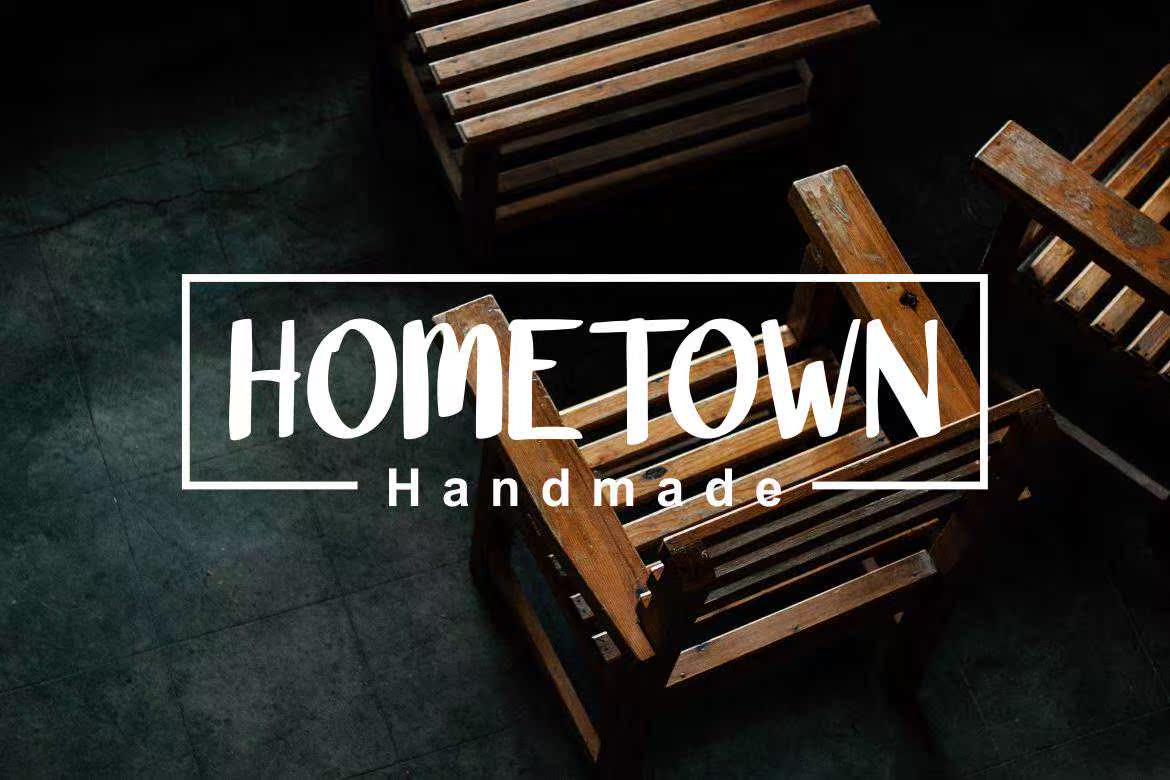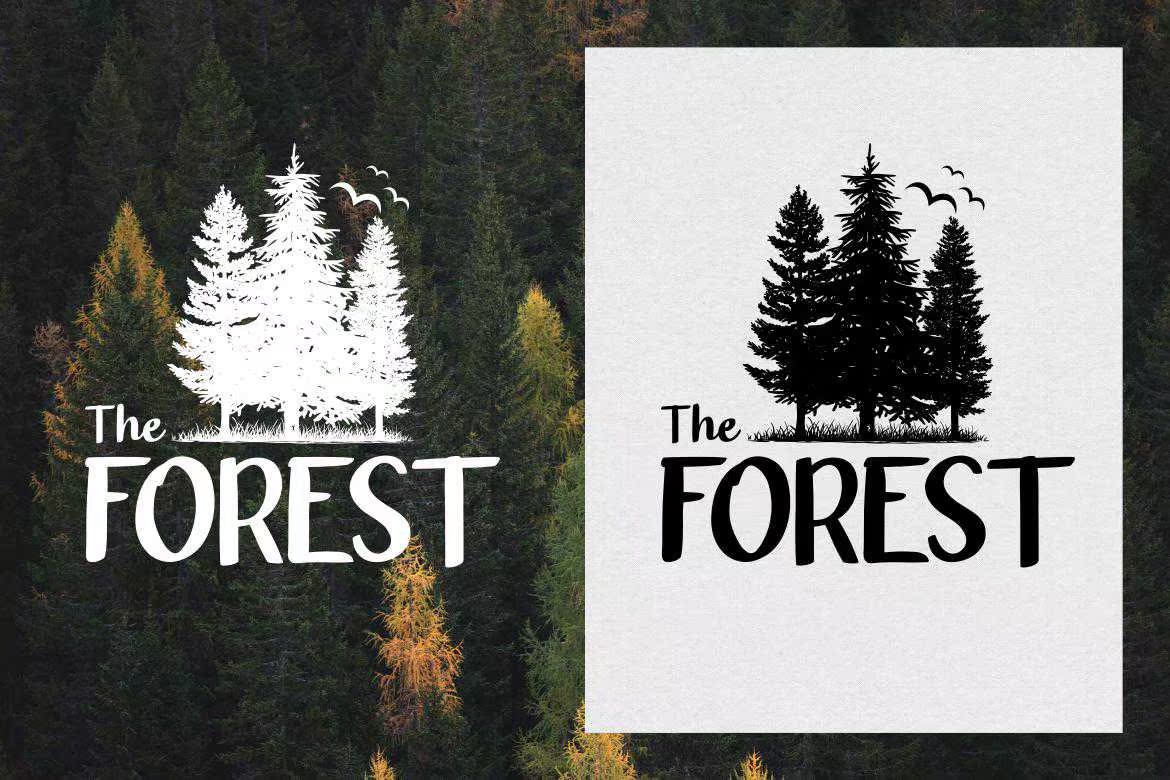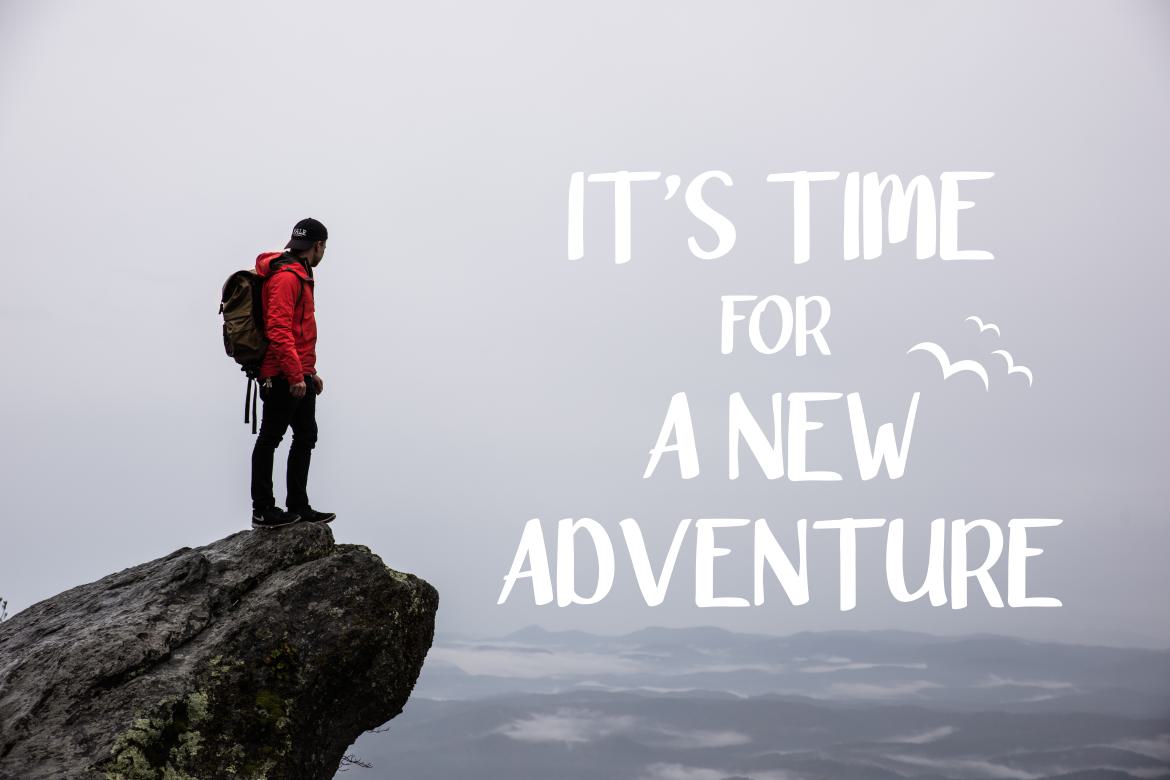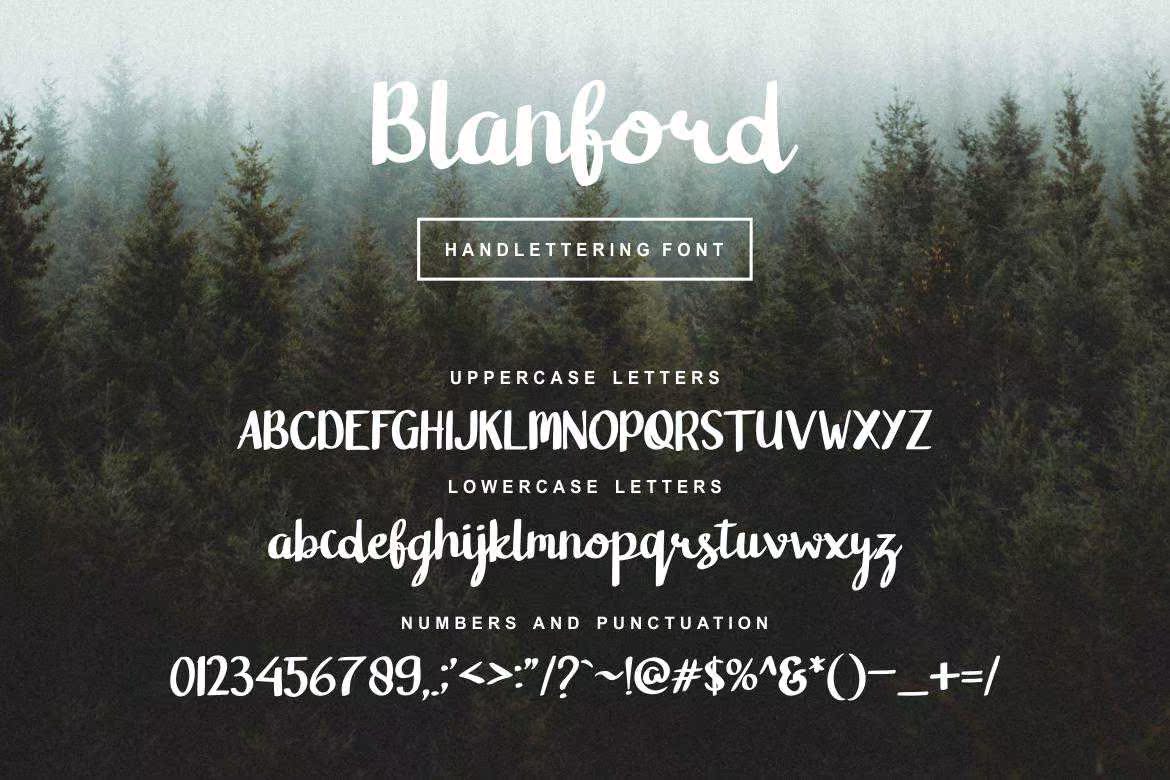
您好……介绍手写字体的平面图。此字体非常简洁、美观。非常适合用于徽标、服装、签名、网页主题、海报、报价、书籍或杂志封面等。您将获得:BlanfordTTF–大写和小写小写字母–标点符号和数字–分隔符和标准符号感谢您的检查,如果您有任何问题或疑问,请在网站上留言。您好…介绍手写字体。此字体非常简洁美观。非常适合用于徽标、服装、签名、网页主题、海报、报价、,您将获得的书籍或杂志封面等;——BlanfordTTF–大写和小写小写字母–标点符号和数字–分隔符和标准符号感谢您的检查,如果您有任何问题或疑问,请访问邮件标题。